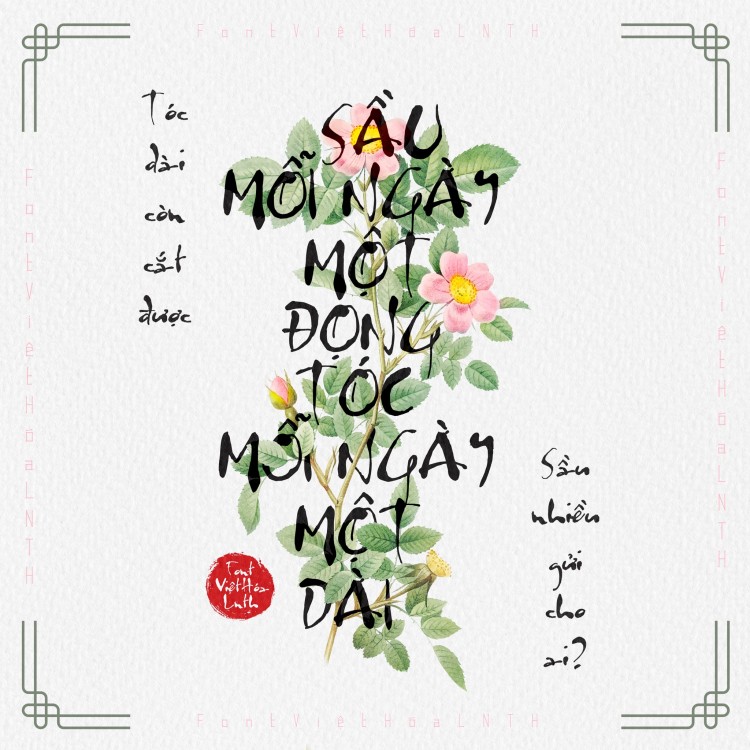
Giới thiệu về bộ Font việt hóa LNTH Watermark
Trong thế giới đồ họa hiện đại, việc lựa chọn một bộ Font Chữ phù hợp đóng vai trò quyết định đến tính thẩm mỹ của sản phẩm. Font việt hóa LNTH Watermark là một lựa chọn tuyệt vời dành cho những ai yêu thích phong cách nhẹ nhàng, tinh tế nhưng không kém phần chuyên nghiệp. Bộ phông này được thiết kế với các đường nét thanh mảnh, uốn lượn mềm mại, giúp tạo nên dấu ấn riêng biệt cho các tác phẩm sáng tạo của bạn.
Đặc điểm nổi bật của Font việt hóa LNTH Watermark
Phong cách thiết kế độc đáo
Điểm mạnh nhất của Font việt hóa LNTH Watermark chính là sự kết hợp hoàn hảo giữa nét chữ viết tay tự nhiên và cấu trúc hiện đại. Các ký tự được chăm chút tỉ mỉ, đảm bảo hiển thị sắc nét trên cả màn hình kỹ thuật số lẫn bản in. Đây là bộ font lý tưởng để làm watermark bảo vệ bản quyền hình ảnh, thiết kế thiệp mời, bìa sách hoặc các dự án nghệ thuật đòi hỏi sự bay bổng.
Tối ưu hóa tiếng Việt hoàn chỉnh
Người dùng tại Việt Nam thường gặp khó khăn khi sử dụng các bộ font quốc tế do lỗi hiển thị dấu tiếng Việt. Tuy nhiên, với phiên bản Font việt hóa LNTH Watermark, toàn bộ hệ thống dấu đã được tinh chỉnh chuẩn xác, giúp văn bản trở nên hài hòa và dễ đọc. Sự ổn định này giúp các bạn học sinh và giáo viên dễ dàng ứng dụng vào việc làm bài thuyết trình hay trang trí báo tường.
Ứng dụng và cách sử dụng hiệu quả
Để phát huy tối đa vẻ đẹp của bộ font này, bạn nên kết hợp với các tông màu pastel hoặc sử dụng trên nền ảnh có độ tương phản cao. Việc cài đặt cũng rất đơn giản, chỉ cần tải tệp tin về và giải nén vào thư mục font của máy tính. Chắc chắn rằng Font việt hóa LNTH Watermark sẽ mang lại làn gió mới cho kho tư liệu thiết kế của bạn. Hãy trải nghiệm ngay Font Miễn Phí, Font Việt Hóa, Font việt hóa LNTH Watermark để tạo nên những tác phẩm ấn tượng và khác biệt nhất ngay hôm nay.